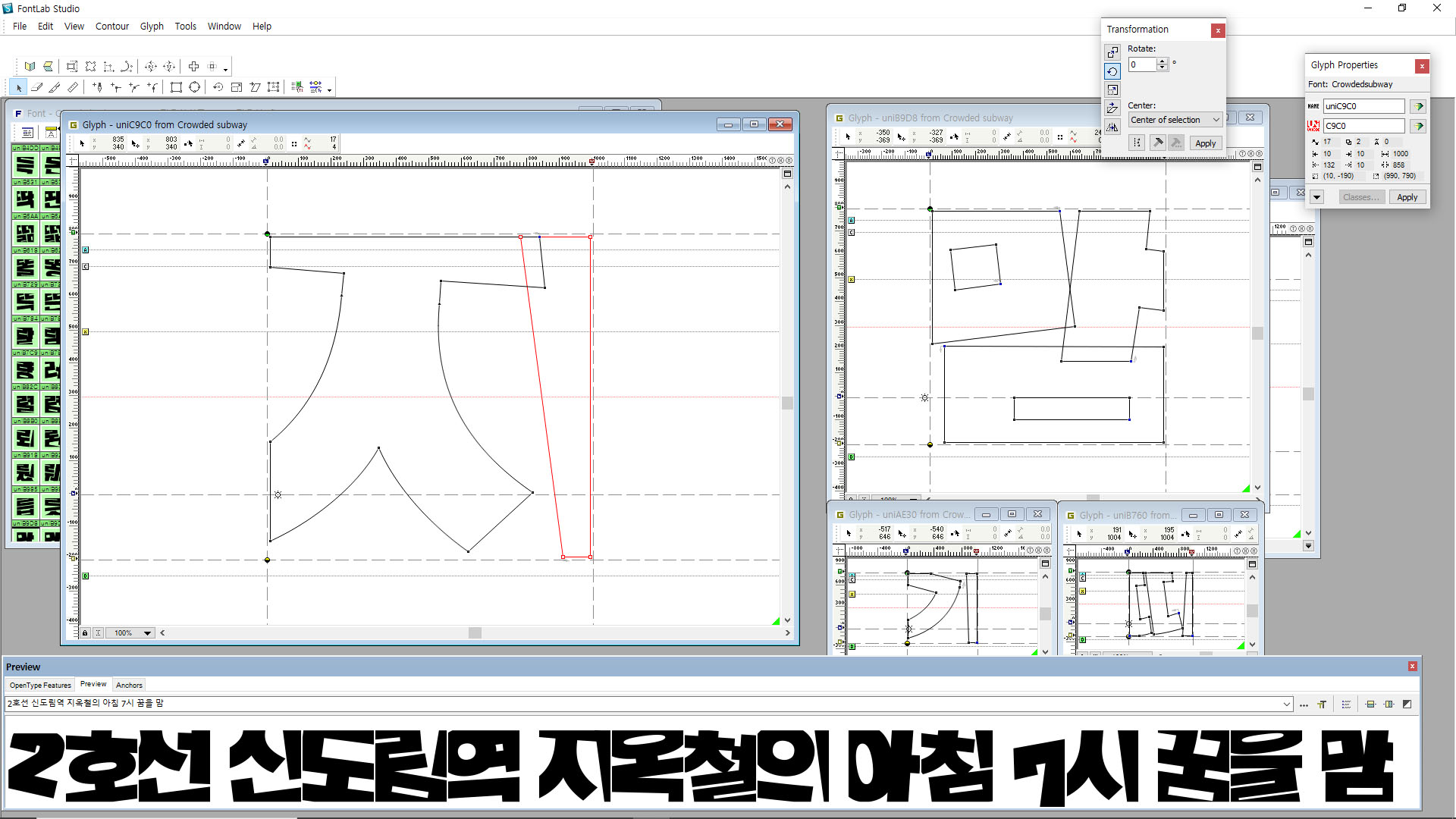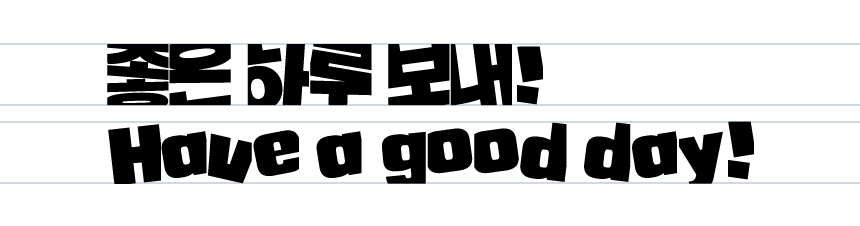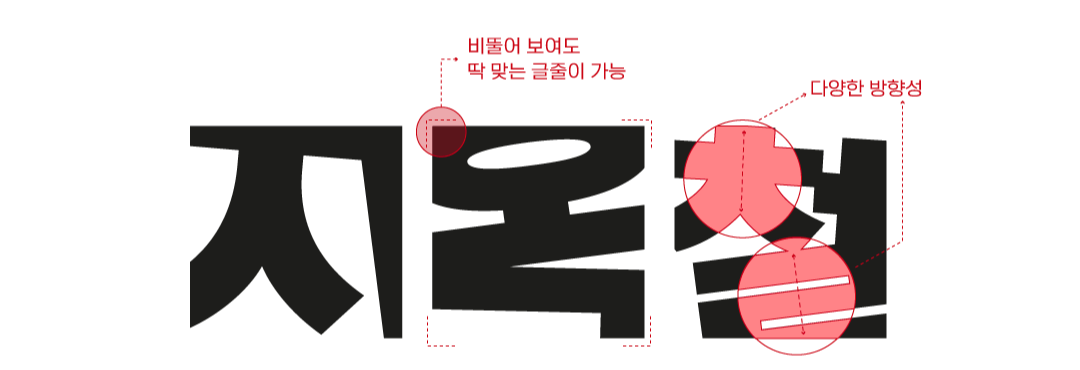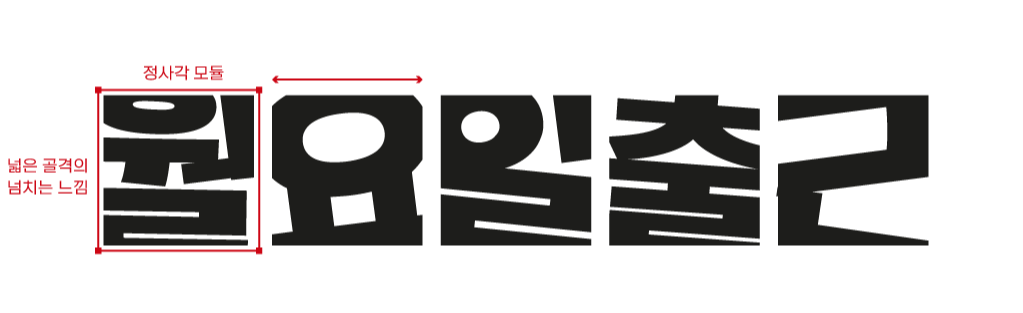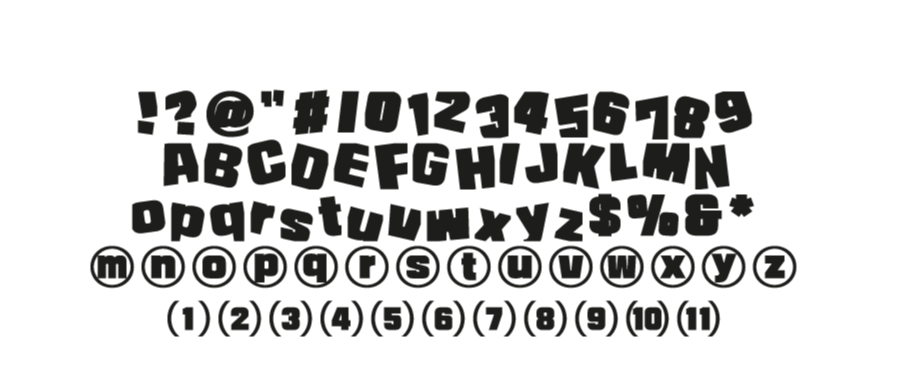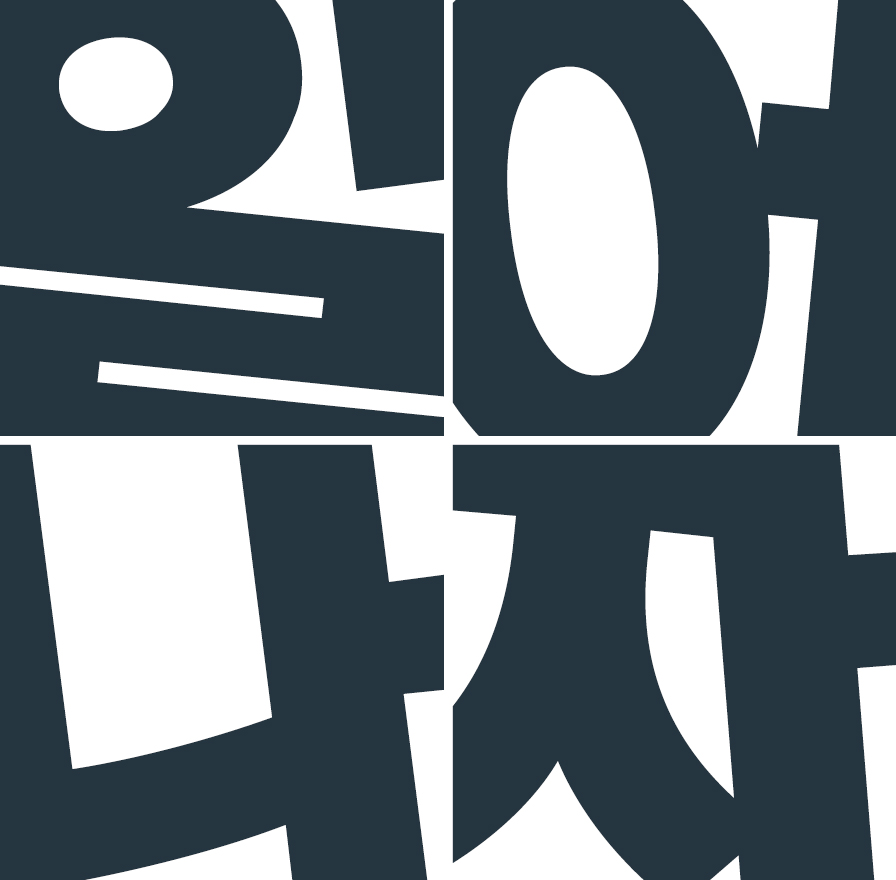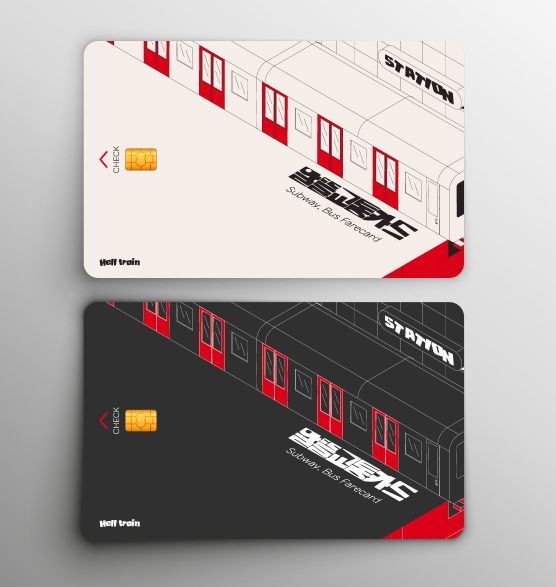
일상의 표정을 담다, Rix지옥철
오늘 출근길은 안녕하셨나요?
대한민국 사람이라면 '지옥철'이라는 단어를 못 들어본 분은 거의 없을 텐데요. 출퇴근길의 지하철에 타는 것을 Hell(지옥)로 표현할 정도로 직장인들에게는 분노와 스트레스를 유발하는 단어입니다. 우리는 이 지옥철을 조금은 다르게 해석해 보려고 해요! '단어가 가진 꽉 막힌 지하철의 풍경을 서체로 표현해서 사람들에게 무료로 배포하면 어떨까?', '부정적인 이미지가 있는 단어에 지하철을 유쾌하게 풀어낸 서체를 통해 재미있는 이미지를 주면 어떨까'라는 생각으로 「Rix지옥철」폰트를 기획하게 되었습니다.
저희는 2022년 새해를 무료 배포 서체로 열고 싶었고, 그 시작을 우리 일상의 한 부분인 지옥철과 함께하기로 했습니다. 힘겨운 하루하루를 보내고 있는 소상공인을 위한 무료 폰트 'Rix열정도체'를 배포한 지 1년여 정도가 지났습니다. 이제 길을 가다 본 간판에서도, 배너나 온라인에서도 쉽게 열정도체를 만나볼 수 있게 되었습니다. 그 마음을 이어가 답답한 마스크를 쓰고 오늘도 지하철에 오르는 직장인들, 평범한 일상을 위해 포기하지 않고 나아가는 모든 분들이 조금은 더 힘을 냈으면 하는 마음으로 무료 폰트 프로모션을 진행합니다. 먼저 폰트를 제작한 김원준 디자이너의 인터뷰를 통해 더 자세한 이야기 들어볼게요!
안녕하세요? 폰트 디자이너 김원준입니다. Rix취중진담에 이어 Rix지옥철로 인사드립니다.
2022년 릭스폰트의 첫 번째 서체로 출시된 Rix지옥철! 이름부터 굉장히 강렬한데 어떻게 기획하게 되셨는지 궁금해요.
이른 아침시간 지하철은 출근하는 사람들로 가득합니다. 가득하다 못해 전후좌우 꽉 막힌 공간은 몸과 마음을 답답하게 합니다. 이런 지하철의 풍경을 글자들로 표현하면 어떨까요? 지옥철은 우리 일상의 한 부분을 표현한 것입니다.
폰트의 특징을 몇 가지 설명해 주신다면?
글자를 늘어놓으면 사람들로 가득한 지하철의 풍경이 떠오릅니다. 박스 안의 자소는 구석구석 밀려 벽에 붙어있는 가지각색의 사람들을 표현한 것이지요. 허락된다면 공간을 탈출하고 싶은 사람들의 마음이랄까요?
제작하는 데 있어 가장 어려웠던 부분이나 신경 쓴 부분?
A. 지하철의 가득 찬 사람들을 자소로 표현할 때 가독성에 대한 부분은 늘 조심스럽습니다. 표현이 앞서면 자칫 읽어내는 것이 어렵기 때문입니다. 과장된 표현은 최소한의 가독을 위한 경계선을 넘지 않아야 합니다.
마지막으로, 사람들이 이 폰트를 어떻게 활용했으면 하시나요?
개인의 취향을 존중합니다!(웃음) 답답한 마음을 표현할 때 편하게 사용해 보세요.
대한민국 직장인을 위한 무료 서체
Rix지옥철은 출퇴근길 고통을 겪고 계신 대한민국 모든 분들을 위해 저작권 걱정 없이 어디에나 사용 가능한 폰트입니다. 용도에 따라 저작권이 다르게 적용되거나 상업용으로는 사용할 수 없거나 하는 무료 폰트도 있죠. 지옥철 서체는 모든 분야에 편하고 자유롭게 사용할 수 있도록 기획하고 제작했습니다.
일상의 표정을 담다
전후좌우 꽉 막힌 출퇴근길 지옥철을 표현한 서체. 흔들거리는 지하철 안에서 샌드위치처럼 포개진 사람들과 다양한 표정들을 네모난 박스 안에 각기 다른 방향성을 가진 자소들로 표현했습니다. 시각적으로 굉장히 비뚤어 보이지만 글줄은 정리되어 보여 가독성을 크게 해치지 않습니다. 굵기는 한 가지로 단단하고 주목도 높은 두꺼운 획이 제목용으로 활용하기 좋습니다.
영문, 숫자, 약물 디자인도 특징을 그대로 반영해 혼용 시 조화롭도록 제작했습니다. 장문의 텍스트로 썼을 때 한글 디자인보다 리듬감 있는 글줄을 느낄 수 있어 더욱 독특하고 재밌는 표현이 가능합니다.
'지옥철'이라는 컨셉에 맞는 디자인 작업에 활용해 보았습니다. 교통카드 스킨, 신용카드 스티커 등 기존의 밋밋한 카드 디자인 꾸며주는 텍스트로 활용하면 어떨까요? 지하철 광고 배너에도 폰트를 사용해 주목도를 높일 수 있습니다.
직장인에게는 커피 수혈이 꼭 필요하죠. 영문으로 쓴 서체의 느낌도 굉장히 개성 있고 유니크하기 때문에 브랜드 로고나 패키지 메인 문구로 활용하기에도 좋습니다. 출퇴근을 알려주는 시계도 없어서는 안 될 필수템🕥
만원 전철의 설렘은 사실 존재하지 않겠지만^^ 이렇게 문구를 넣은 일러스트 폰 케이스 등 다양한 굿즈에 재밌는 디자인으로 활용할 수 있습니다. 가시성이 좋고 다방면으로 활용도가 높은 서체입니다.